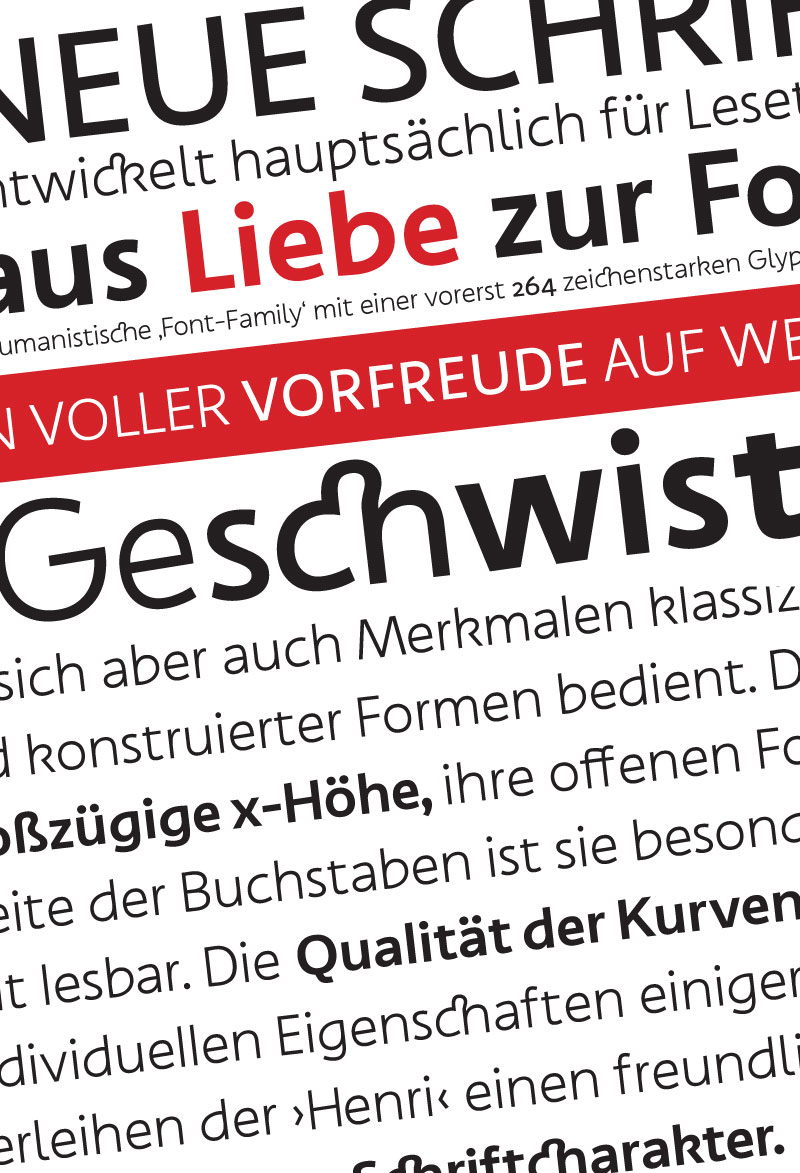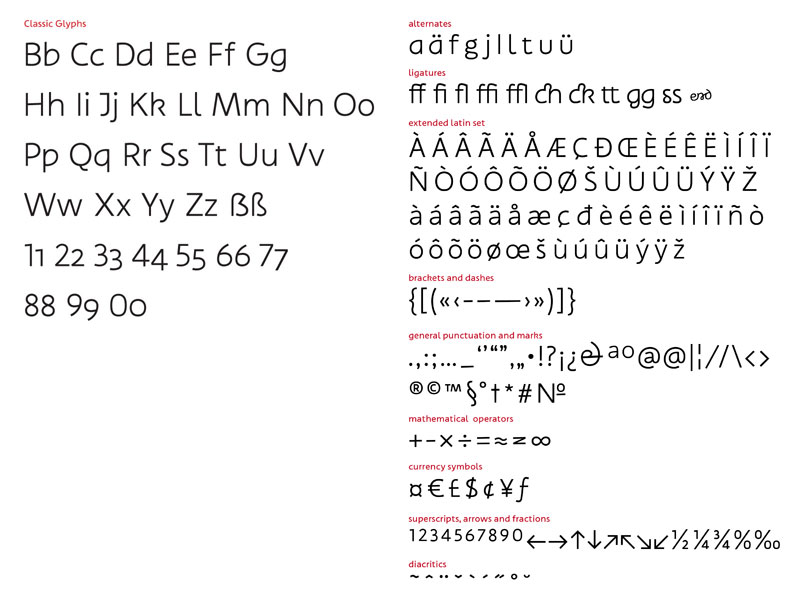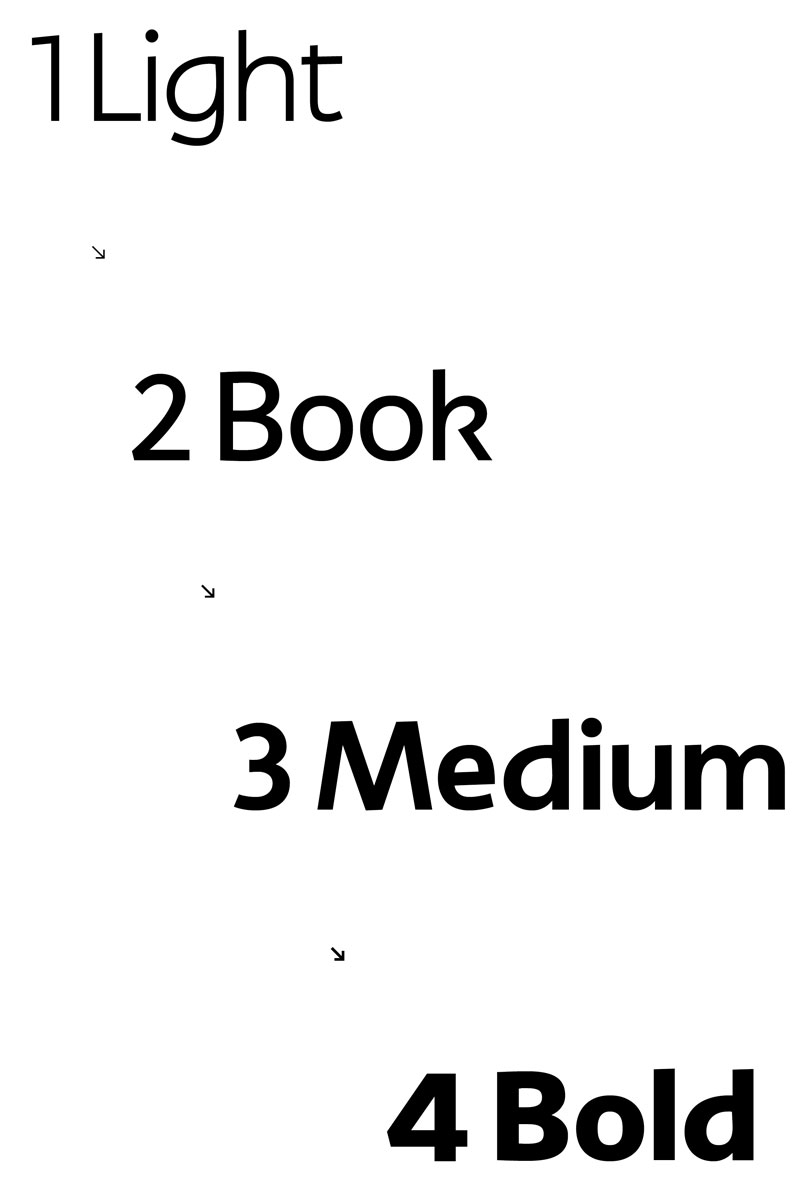
Die sansitive Schrift Henri ist im Jahr 2012 von Lisa Krack im Rahmen einer Bachelorarbeit unter der Betreuung von Luc(as) de Groot, entwickelt worden. Zweck der Schriftentwicklung einer serifenlosen war das testen und schulen des Gespürs für Kurven und Proportionen der Gestalterin. Daneben sollte die Henri gut lesbar sein. Bei der Gestaltung wurden aus diesem Grund Erkenntnisse aus der parallel entstandenen theoretischen Arbeit Anforderungen an die Gestaltung einer Leseschrift berücksichtigt.
Trotz Rationalisierung der Strichstärken, also geringem Kontrast, ist dieses Ziel erreicht worden. Dazu tragen vor allem die große x-Höhe mit den daraus resultierenden großen Buchstabeninnenräume bei, sowie die offenen Formen aller Zeichen. Durch die komprimierten Ober- und Unterlängen wird eine klare Zeilenbildung erzeugt, die sich – neben eines gleichmäßigen Grauwertes des gesamten Schriftbildes – vorteilhaft auf die Leserlichkeit auswirkt.
Die Buchstaben der Henri weisen an unterschiedlichen Stellen vom Schreiben und vom Schreibwerkzeug beeinflusste Formen auf (z. B. die Kurven von b und d oder die angeschrägten An- bzw. Endstriche von h und c). Als Besonderheit kann das kleine l gelten, dass mit seinem gebogenen Bein zusätzlich der Lesbarkeit dienlich ist. Auch das G ist anders als üblich gestaltet: die weiter fortgeführte Kurve, die in einen ebenso untypischen Querstrich mündet, ist eine Interpretation des weichen Formcharakters der Schrift und unterstützt ihren menschlichen Antlitz. Die verschatelten Varianten des K und R sind unter Vertretern des Genres der humanistischen serifenlosen Schriften außerdem selten gesehen, fügen sich aber dennoch mit der Vertrautheit ihrer Formen ohne Aufsehen in das Schriftbild ein. Des weiteren stellt das kleine k ein weiteres individuelles Merkmal dar, dessen Form dem Charakter entsprechend gewählt wurde. Zudem greift sie einmal mehr die Beeinflussung der vom schreiben kommenden Formen auf.
Nüchtern und Gesichtslos ist die Henri in keiner Hinsicht, was der Leserlichkeit keinen Abbruch tut. Sie erzeugt ein freundliches Schriftbild und kann für unterschiedliche Zwecke eingesetzt werden. Ihre Vollständigkeit, ein optimales Kerning, viele Features sowie zusätzlie Schnitte und Glyphen (mit vielen Ligaturen und nützlien Symbolen) sind in der Zukunft geplant. Bisher verfügt die Henri über 4 Gewichte.
Henri – a new sansitive Typeface